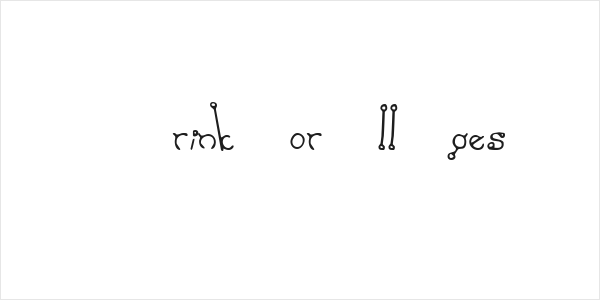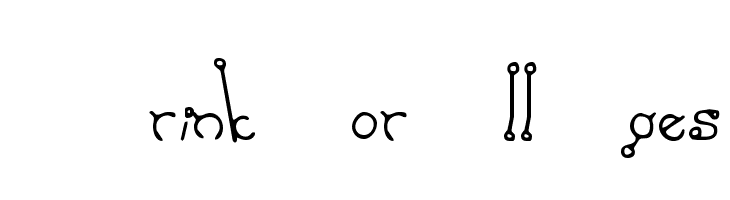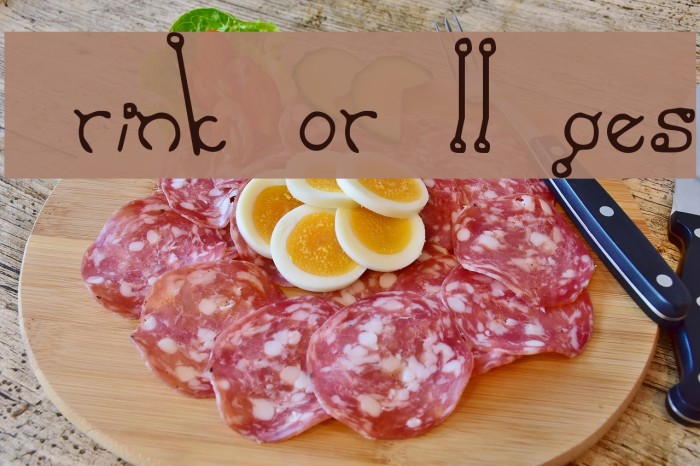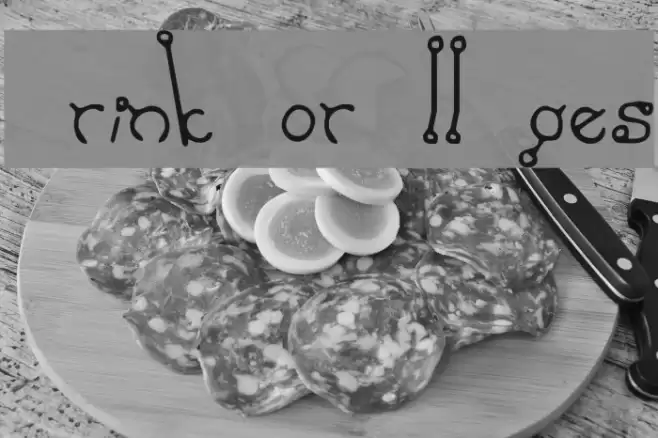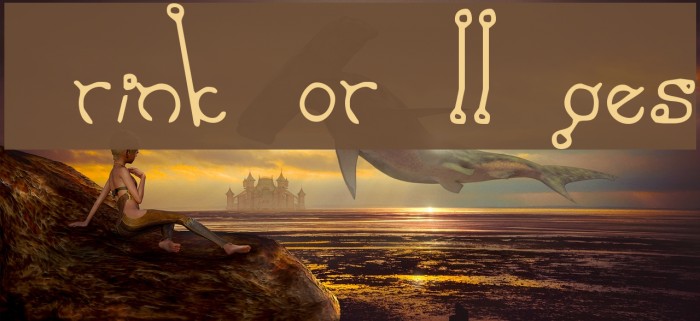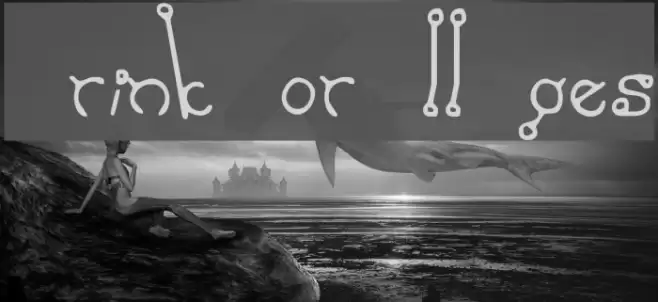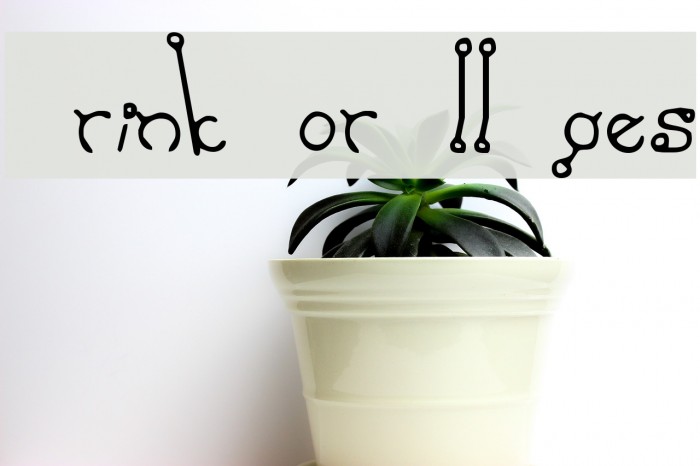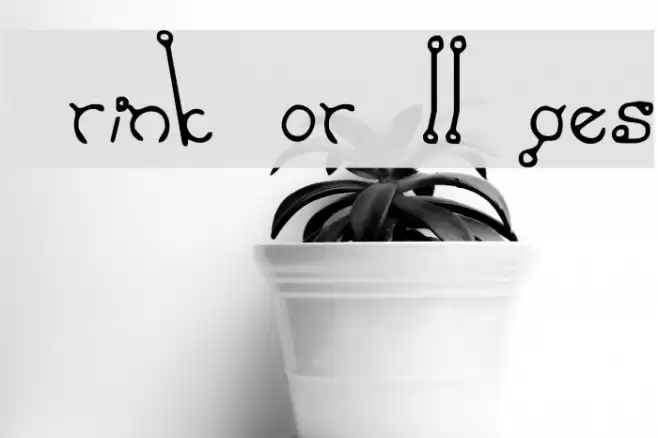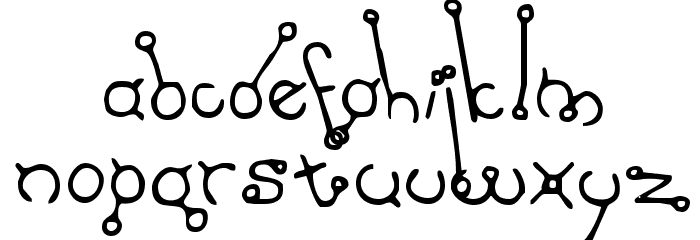
A Drink For All Ages Font
✎ Decorative
| Gesamtstil | Futuristic, Artistic |
| Anwendungsfall | Logos, Posters, Creative Branding |
| Vorgeschlagene Projekte | Tech-themed posters, innovative product branding, creative digital art, futuristic event invitations. |